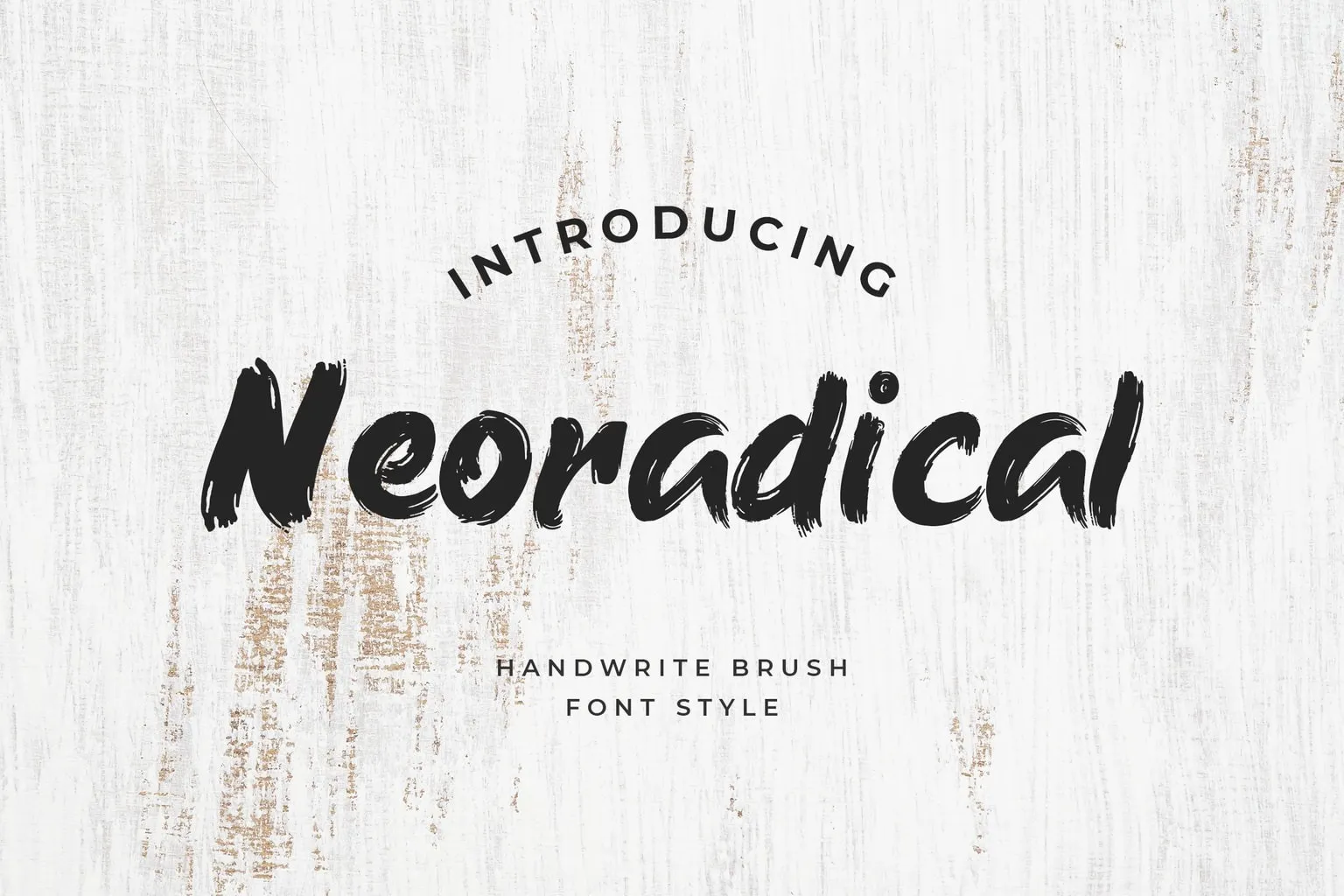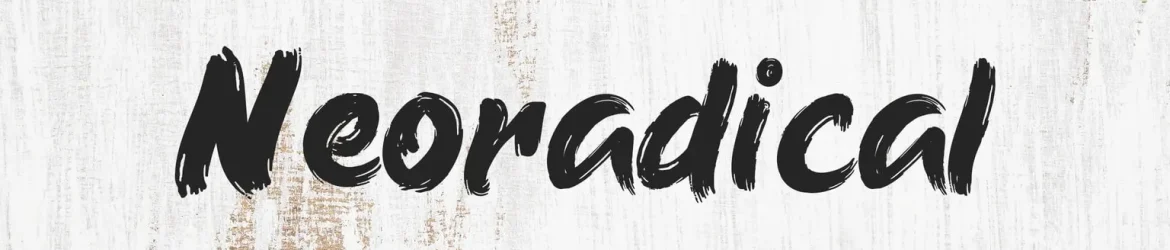
Esta font ‘Neoradical’ é um elegante traço desenhado a mão, com textura metálica que faz surgir projetos com aparência autêntica. A criação de uma linguagem visual arredondada e fluida foi feita por designer da 99designs, UI Creative. O Neoradical se destaca por seu estilo moderno e atraente, fornecendo um aspecto natural ao texto ao mesmo tempo que mantém uma aparência moderna e moderna. É perfeito para uso em qualquer aplicação gráfica, incluindo logo criação, marca identidade visual, design editorial, arte de produto, capas para revistas e mensagens visuais. Com um traço fino, mas ainda assim atraente e harmônico, o Neoradical é uma escolha perfeita para qualquer projeto que precise de um estilo elegante e contemporâneo.